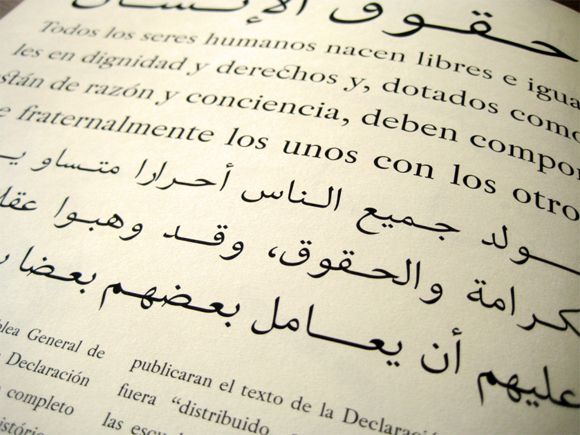
Los European Design Awards premian anualmente lo mejor del diseño gráfico, interactivo e ilustración en Europa. Entre los galardonados de este año se encuentra el diseñador tipográfico Andreu Balius que ha conseguido un premio por su tipografía Al-Andalus.
Al-Andalus es una tipografía árabe creada para favorecer el intercambio entre culturas en España. Incluye un completo juego de caracteres tanto para la escritura árabe como para la latina. Los caracteres árabes también incluyen todos los glifos para su uso con el Farsi y el Urdu, así como un completo juego de ligaduras y signos de puntuación.
Para el latín dispone de un conjunto de caracteres extendidos, números, ligaduras y símbolos extras (incluidos ornamentos).
Pensamos que es un trabajo con una gran carga conceptual con un objetivo claro de mestizaje y para el autor un auténtico «tour de force» ya que las grafías árabes están totalmente alejadas de las latinas y no es fácil afrontar su diseño y producción.